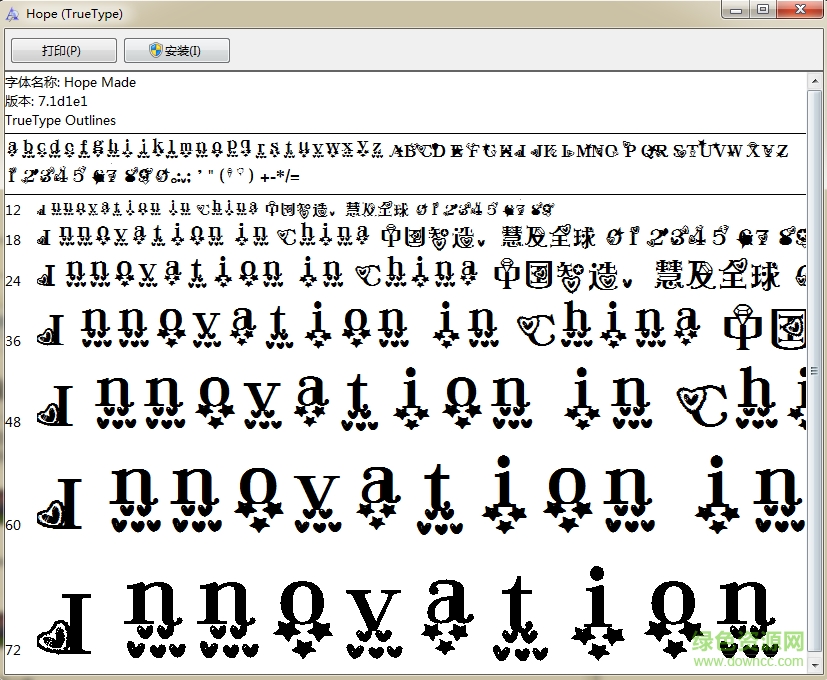
鉆石連環(huán)心是網(wǎng)友制作的一款趣味可愛(ài)的藝術(shù)字體,以鉆石、心形圖案來(lái)為你的字做點(diǎn)綴,更顯生動(dòng)活潑,喜歡的朋友就來(lái)綠色資源網(wǎng)下載吧!
鉆石連環(huán)心是一款在造型生動(dòng)的鉆石字體,讓你的文字彰顯鉆石和桃心的獨(dú)特魅力,歡迎大家免費(fèi)體驗(yàn)!